22款简约手写风格的英文字体
Jenna Sue
一个漂亮到可以做签名的手写英文字体,如果你还没英文签名,那么可以参考这个字体的写法,超看好!
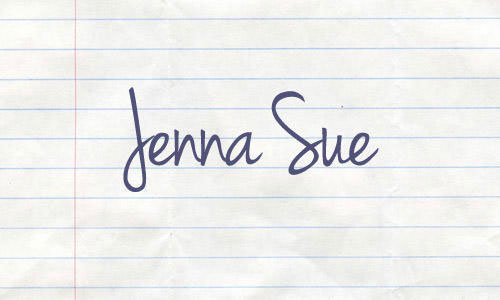
Hand Of Sean
大胆加粗的字体线条,类似一种记号笔的笔触已定而成,用于做标记或许很不错。
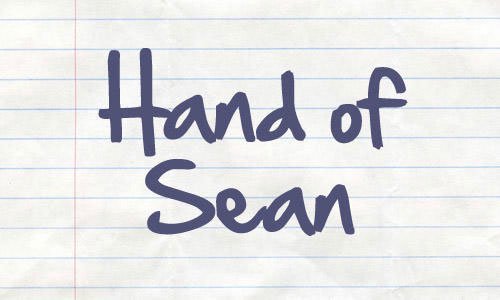
Daniel
一个看起来轻快的字形,不潦草,容易辨认。
GoodDog
这是一个有些卡通、童趣感的字体,并且使用了超粗的细条,非常适合做banner广告的字体。
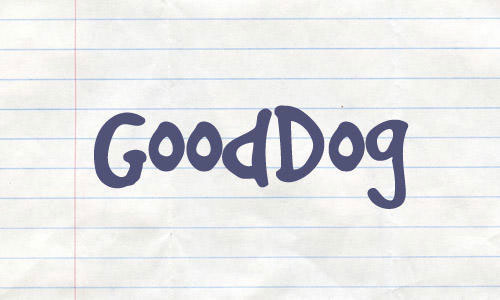
Sweetly Broken
这是一款甜美的字体,直接可以有你优雅的设计作品锦上添花。
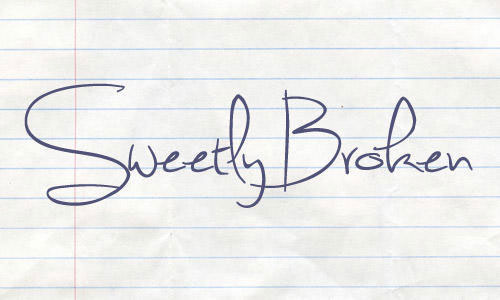
Lovely Eunike Hans
算是比较「工整」的手写字母,比如用来做黑板字,感觉不还可以,你觉得呢?
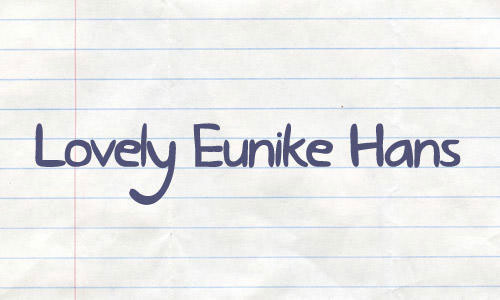
Angelina
另一个优质手写字体,优雅整洁,大小写都很好看。
Journal
又一款非潦草字体,多个选择不错。
Jinky
这个字体的排版不是太工整,但又不算潦草,看起来有些趣味性。
Throw My Hands Up In The Air
落笔与笔尾有重轻,收笔自如,果真每一个人都有不一样的字体特征。
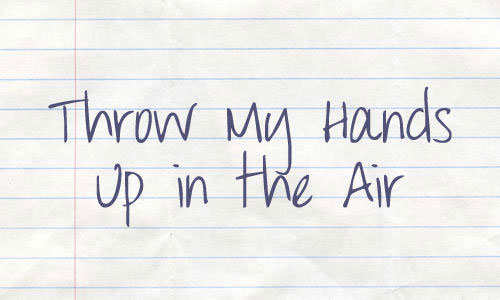
Christopher Hand
这是比较少数的手写风,也许你缺少了这种字体!
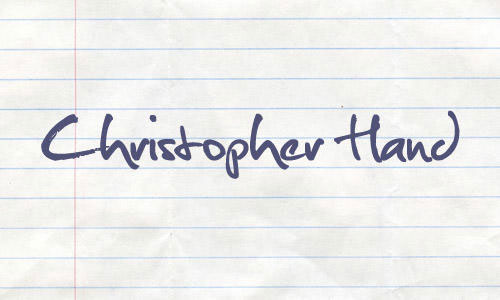
Joy Like Sunshine Through My Windowpane
这是一个拥有长名字的字体,并且很好描述了这个字体的韵意,透过玻璃窗欣赏阳光的快乐。
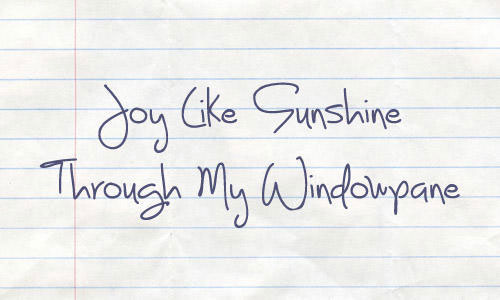
The Great Escape
Akbar
有些特别的手写风,大小写字母的细条粗细是不一样的。
Talking To The Moon
有些像女生写的字体,优雅而工整。
Dear Joe
简约优雅的风格,个别字母大小对比强烈。
Gunny Rewritten
这个英文字体的收笔很有意思,有点类似与中文字的笔峰,但它没有中文字的修长。
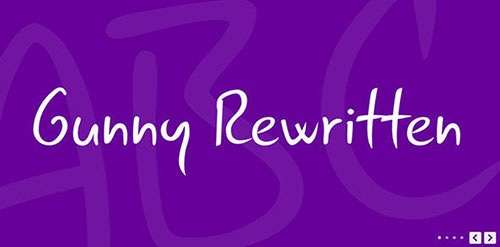
Skinny
模拟细线的手写字体,轻、薄、瘦,很有意思。
A Year Without Rain
一年没有雨。
Yank
如果你在寻找一款很酷的字体,我想这个很适合你,像是用钢笔工具来绘制Yank字型。
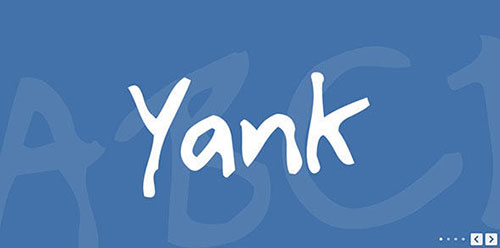
Faraco Hand (As Seen On Line25!)
又一款很好的字体,请你收藏好它。